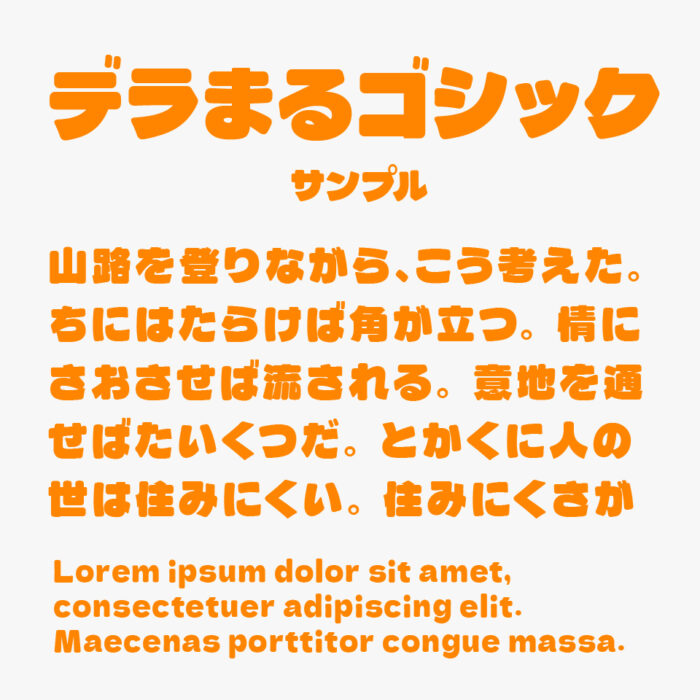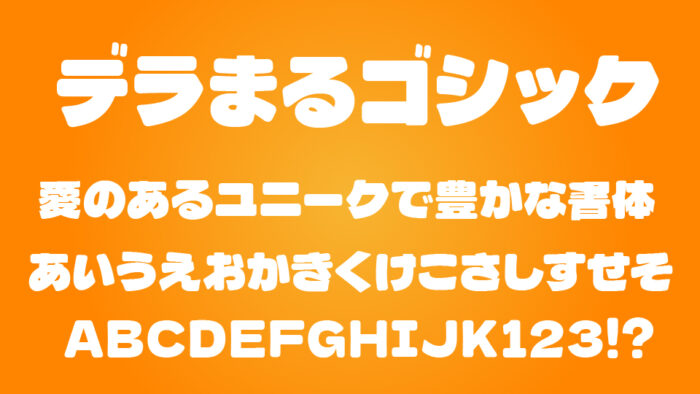
デラまるゴシックフォントは、デラゴシックをベースして、角を丸く加工を施している丸ゴシック体フォントです。
コロンとした極太のシルエットが、陽気で明るくパワフルな印象があるフォントです。デラゴシックのインパクトはそのままで、柔らかく可愛らしい仕上がりとなっています。
| 漢字 | ○(JIS第一〜第三水準漢字まで収録) |